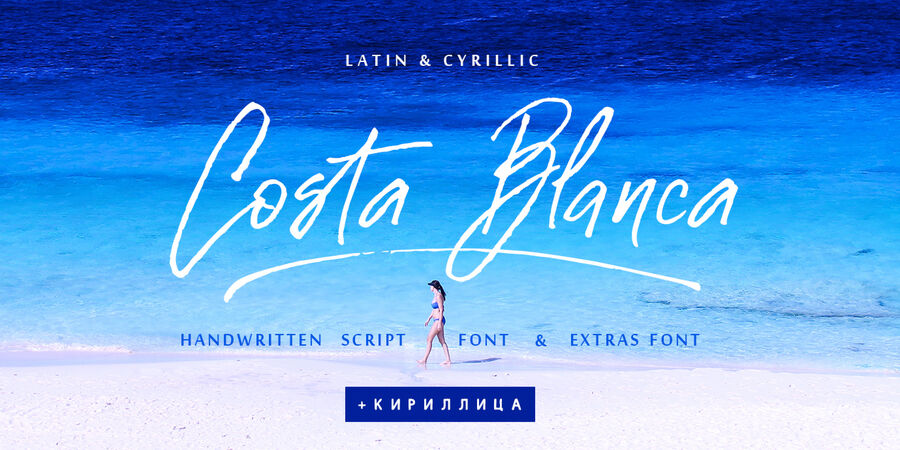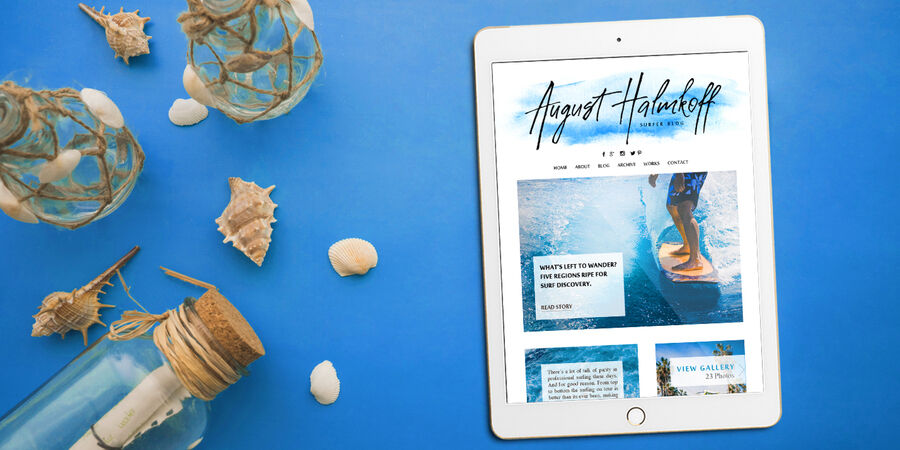
Рукописний текстурний шрифт Коста Бланка був написаний колапеном і чудово підійде для дизайну брендів, плакатів, одягу, логотипів, заголовків веб-сайтів, дизайну одягу, дизайну весільних листівок і багато чого іншого.
Намальований вручну шрифт Коста Бланка містить повний набір великих літер і 2 повних набори малих літер і 36 лігатур, які можна використовувати для створення каліграфії. Використовуйте рядкові та дволітерні лігатури, що чергуються, щоб надати своїм творінням ідеального вигляду ручного письма.
Кирилична частина шрифту містить повний набір великих і малих літер, а також 17 лігатур, що надають реалістичний стиль вашій типографії.
Шрифт розробила Ірина Двілюк у 2021 році.
неформальний, радісний, свіжий, повітряний, швидкий, динамічний, натхненний, ліричний, чуттєвий, емоційний, музичний, поетичний, артистичний, пристрасний, творчий, лихий, розв'язний, сміливий, оригінальний, вільний, самобутній, різкий, колоритний, живий, темпераментний, моторний, розмашистий, літній, характерний, святковий, романтичний, ритмічний, легкий, жіночий, мажорний, вітряний, танцюючий, цікавий, красивий, елегантний, жіночний, епістолярний, крафтовий, сексуальний, художній, симпатичний, худий, летячий, біжить, зелений, модний, щасливий, рукотворний, ручний, екологічний, довірчий, натуральний, природний, рухливий, ламповий, здоровий, бадьорий, побутовий, вернакулярний, дитячий, наївний, грайливий, легковажний, інтимний, сентиментальний, гарненький, артізанальний, рослинний, дівчачий